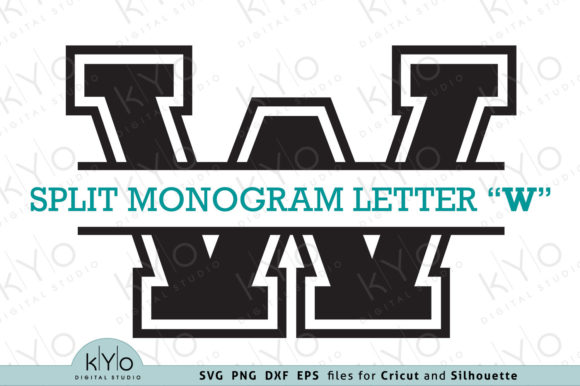
Unique Split Monogram Font Letter W
Mencari elemen reka bentuk yang sesuai boleh menjadi mencabar, tetapi Unique Split Monogram Font Letter W menawarkan koleksi luar biasa yang menaik taraf karya anda serta-merta.
Dicipta dengan ketepatan, Unique Split Monogram Font Letter W menyediakan vektor yang bersih, tipografi yang licin dan lesen komersial untuk ketenangan fikiran.